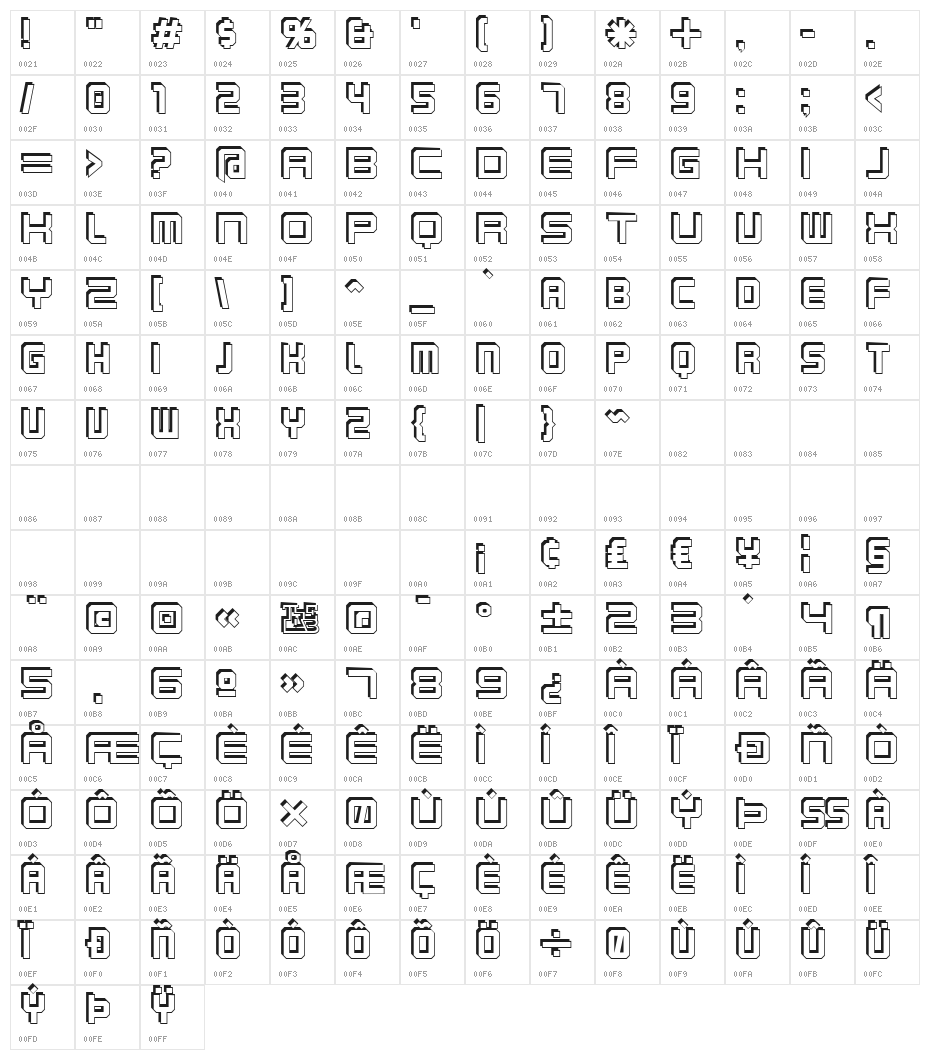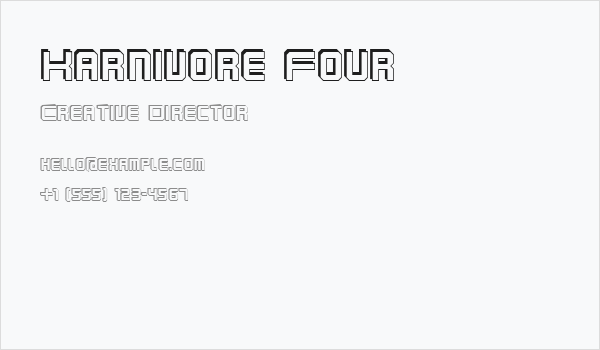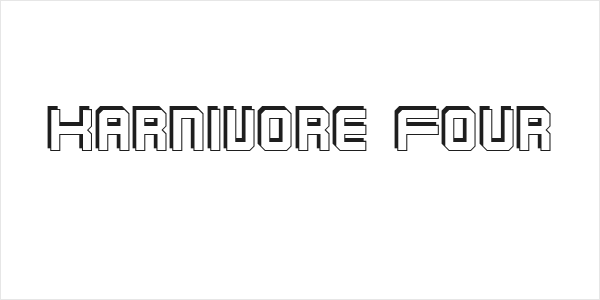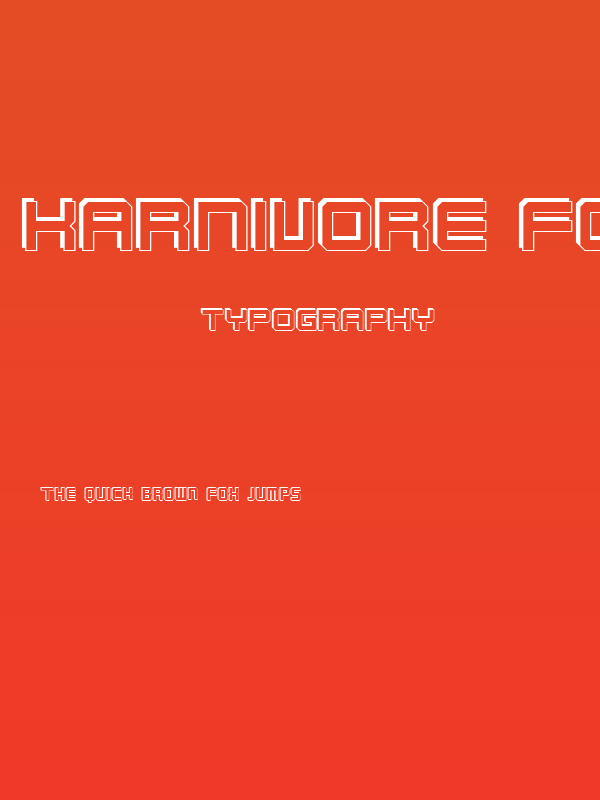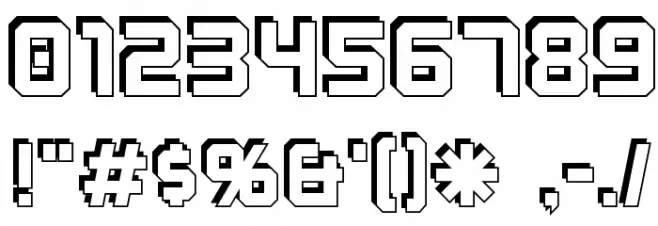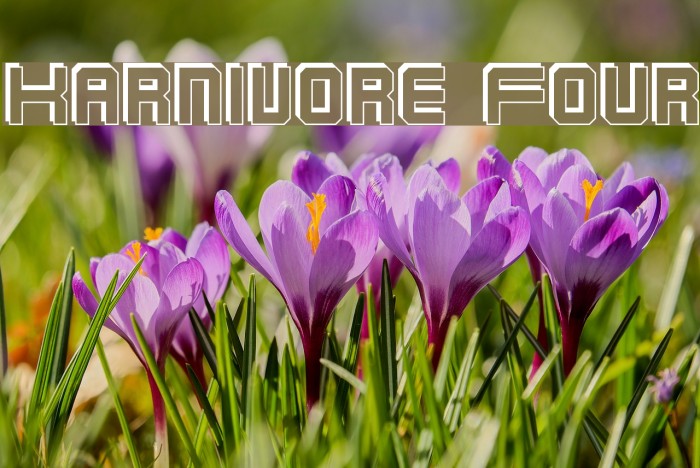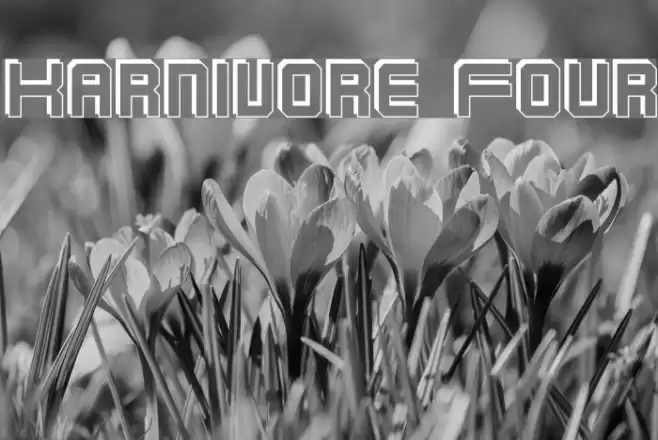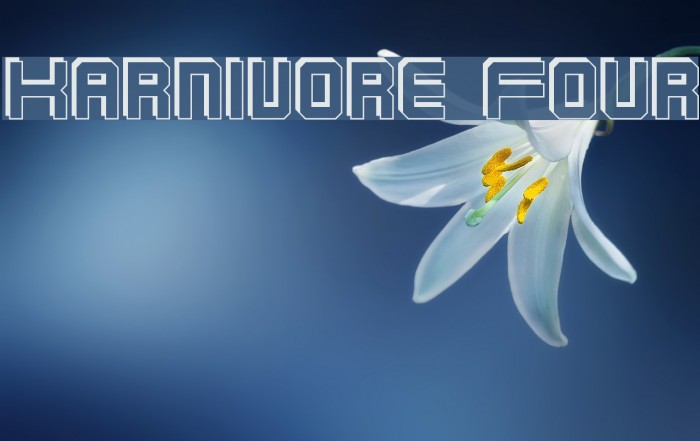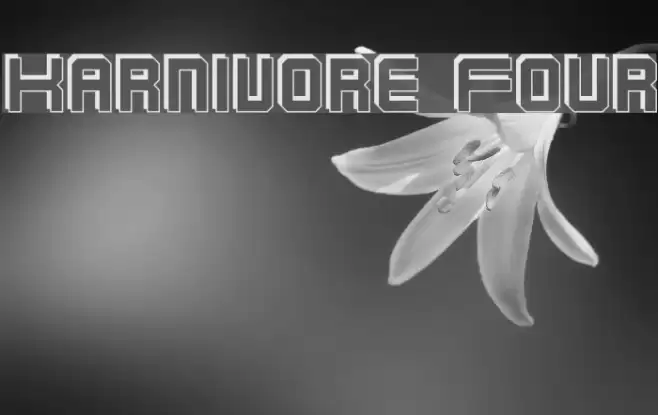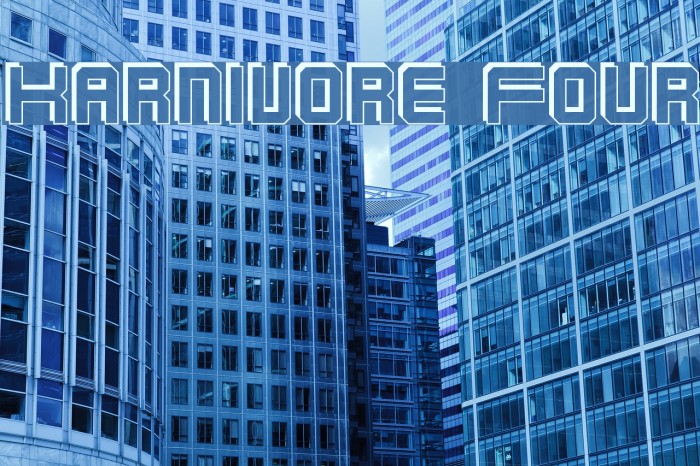
Karnivore Four Font
| カテゴリ | 3D |
| 全体的なスタイル | Futuristic, Industrial |
| おすすめプロジェクト | Ideal for video game titles, movie posters, branding for tech companies, or any project needing a futuristic and bold look. |